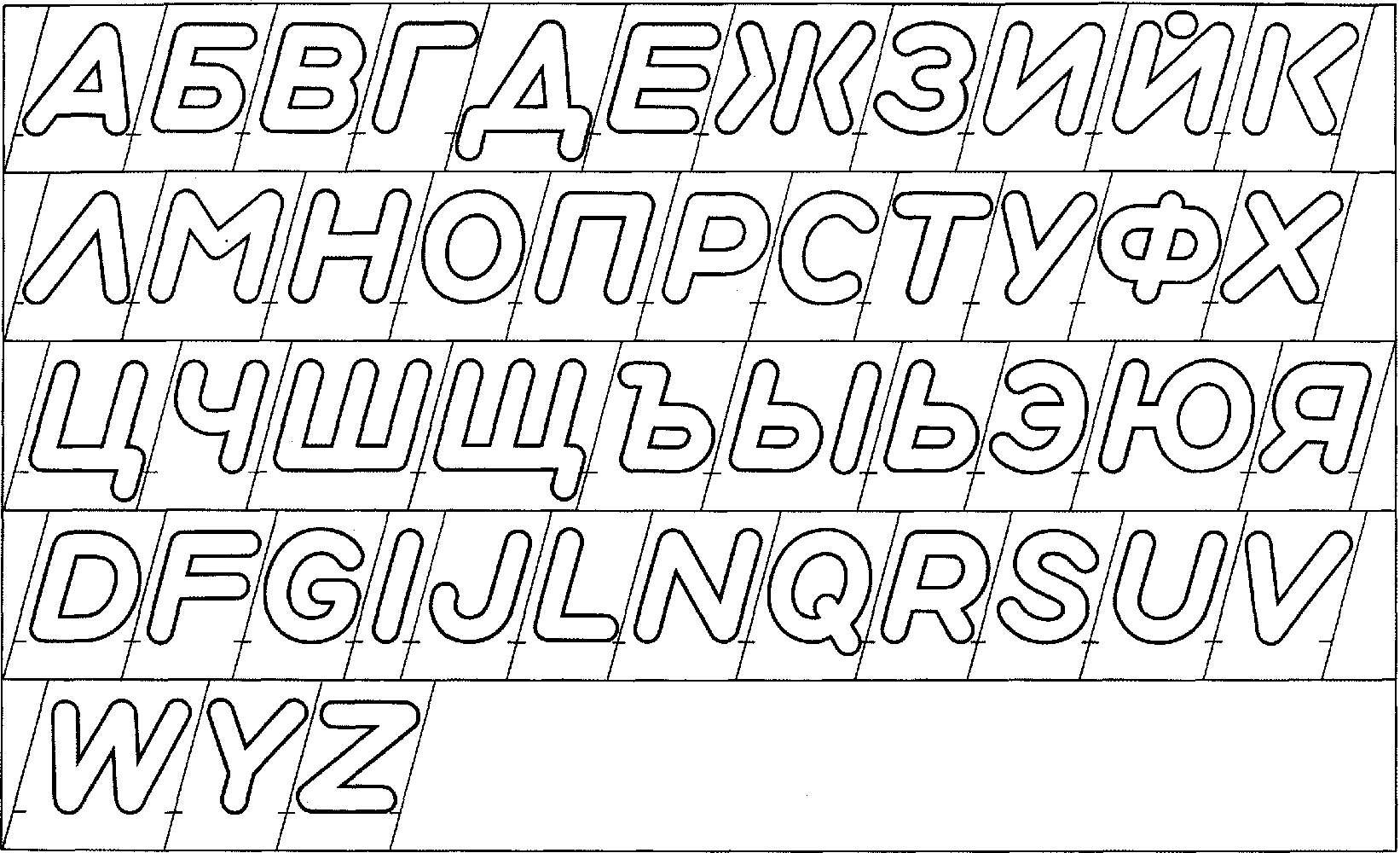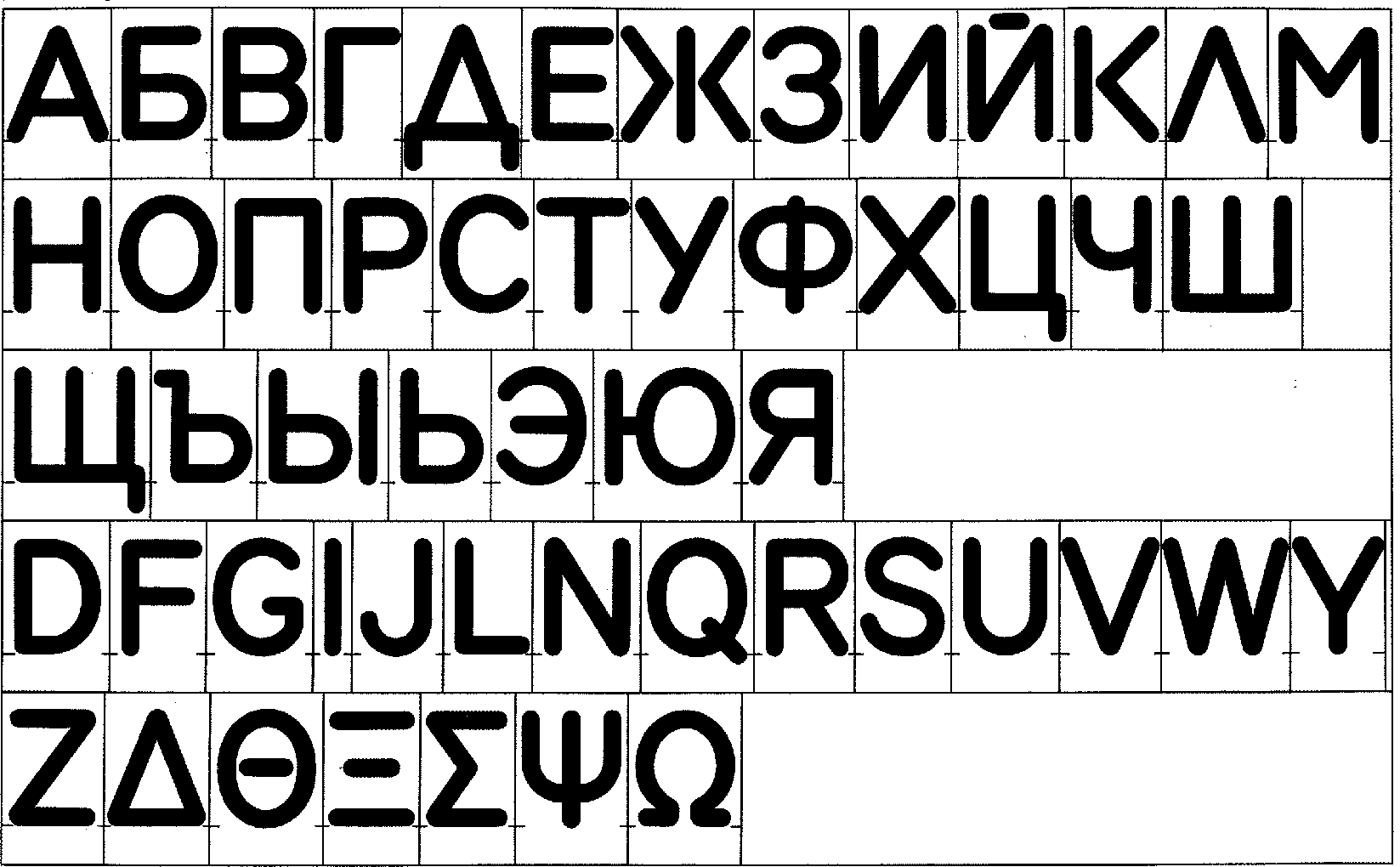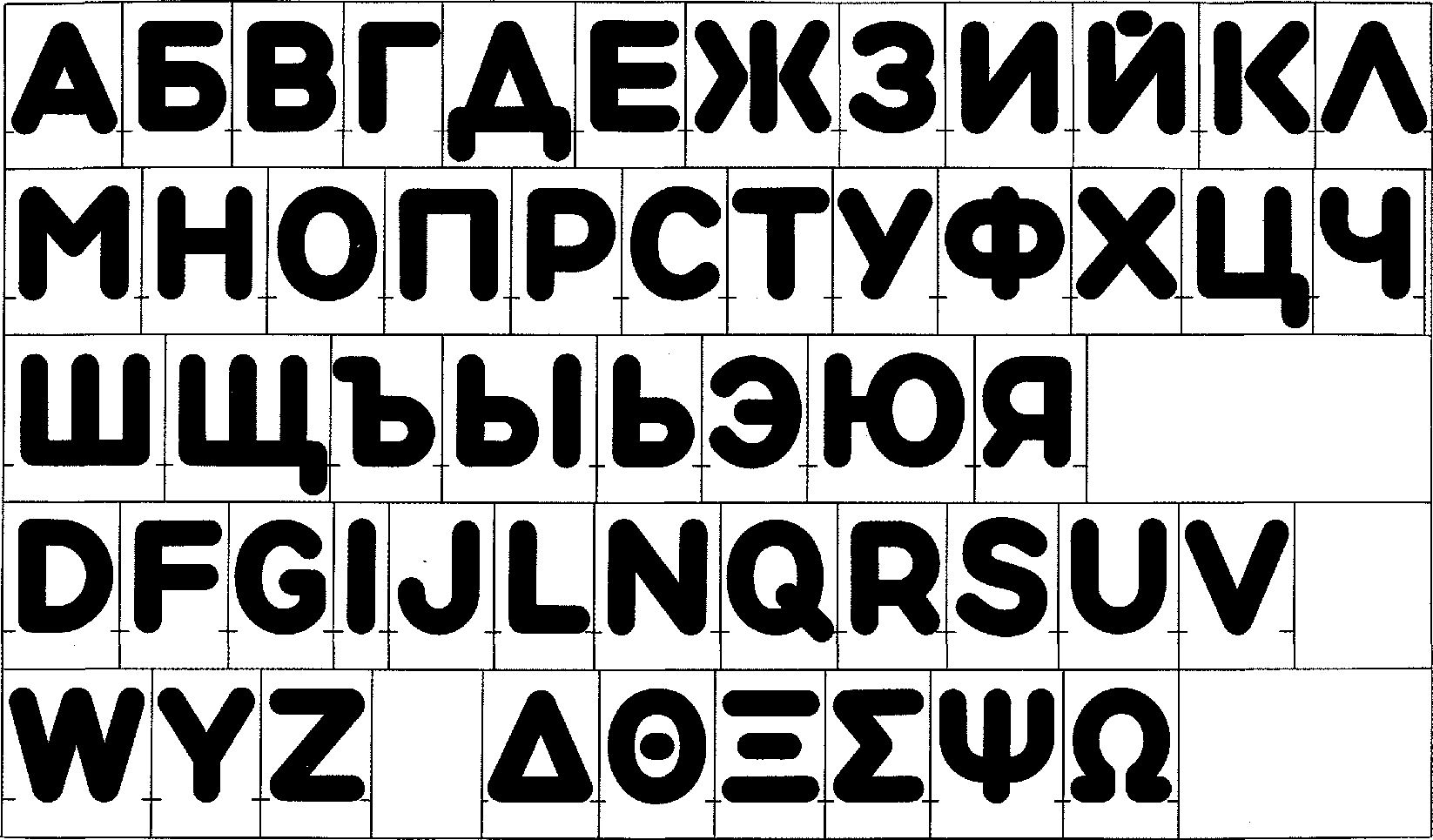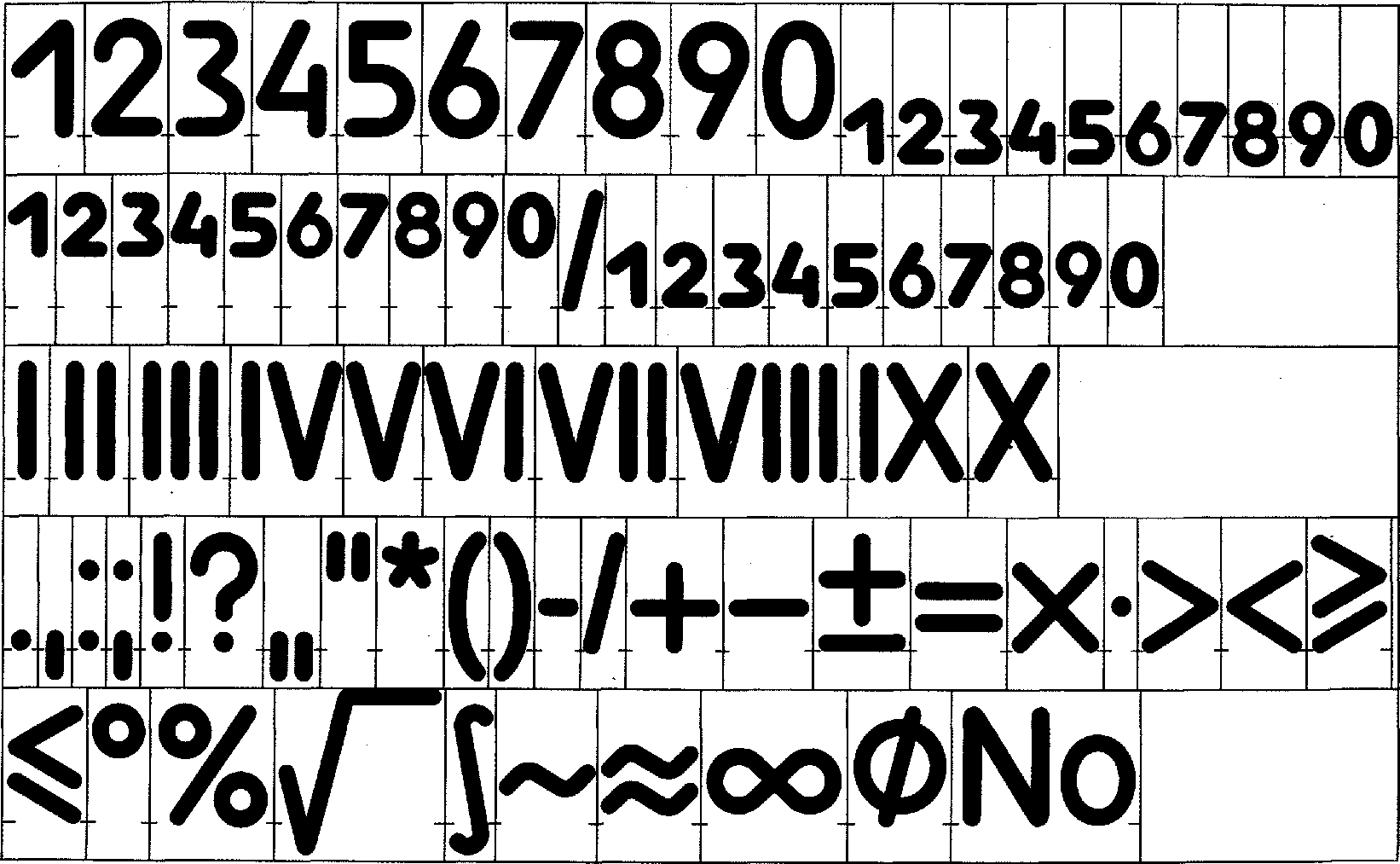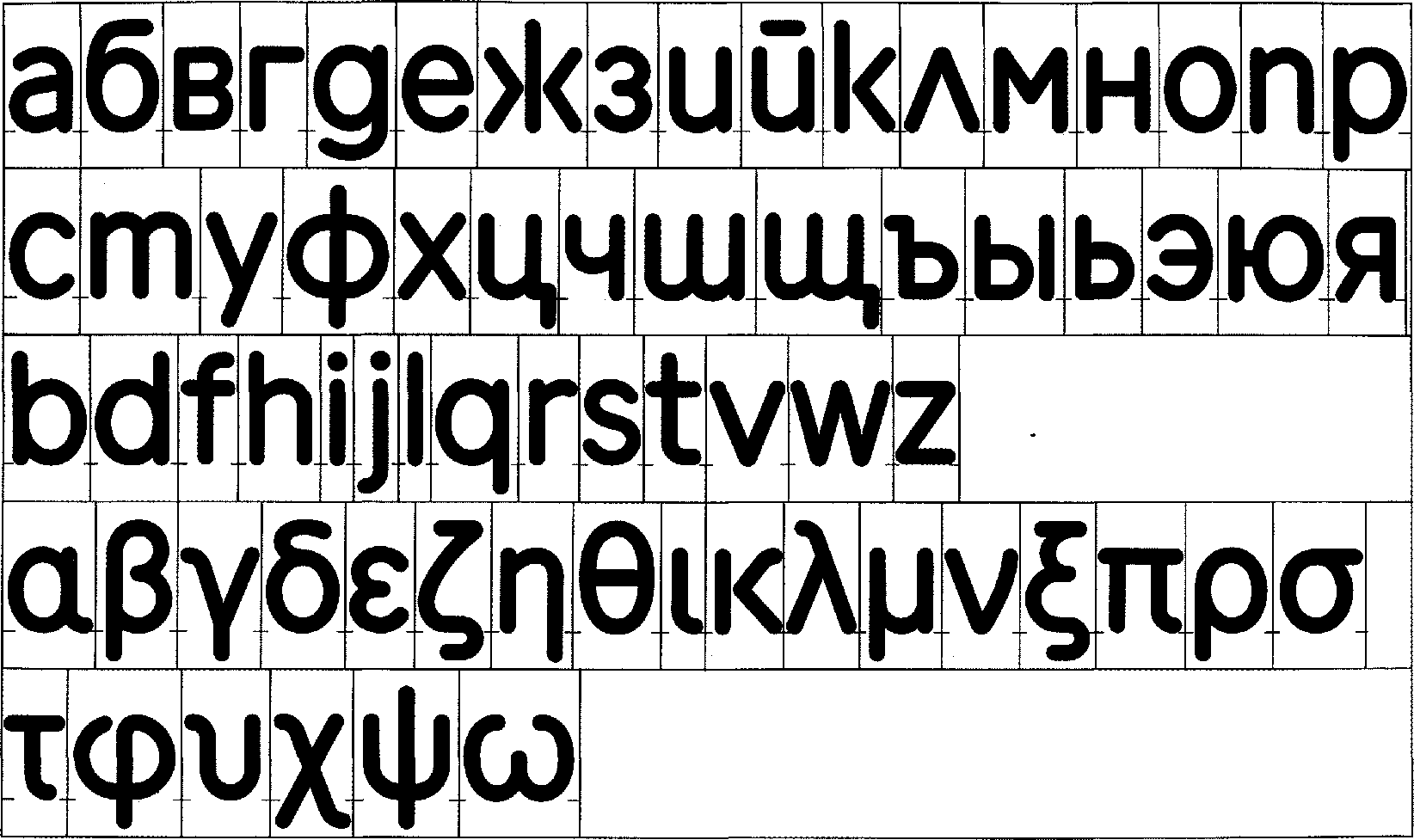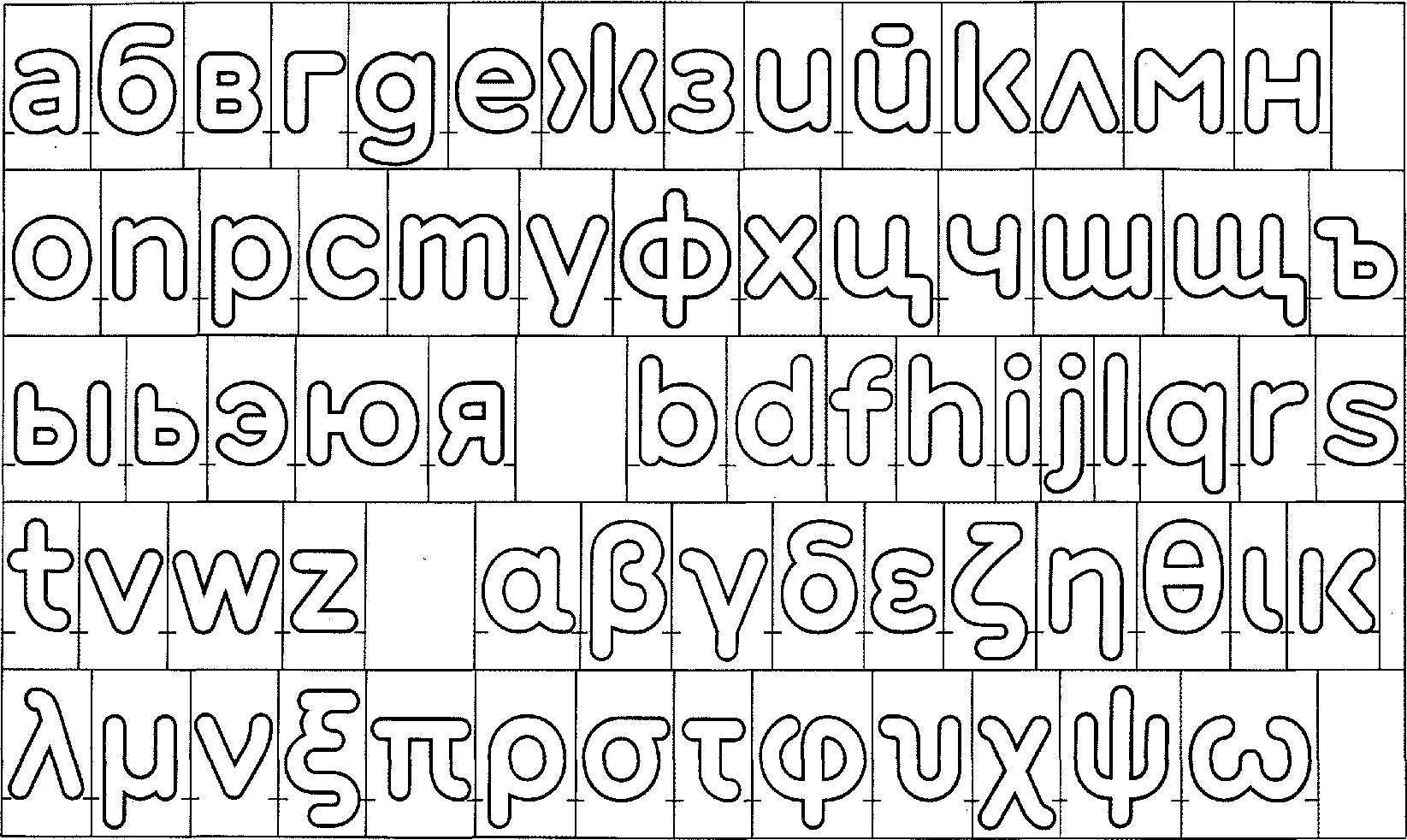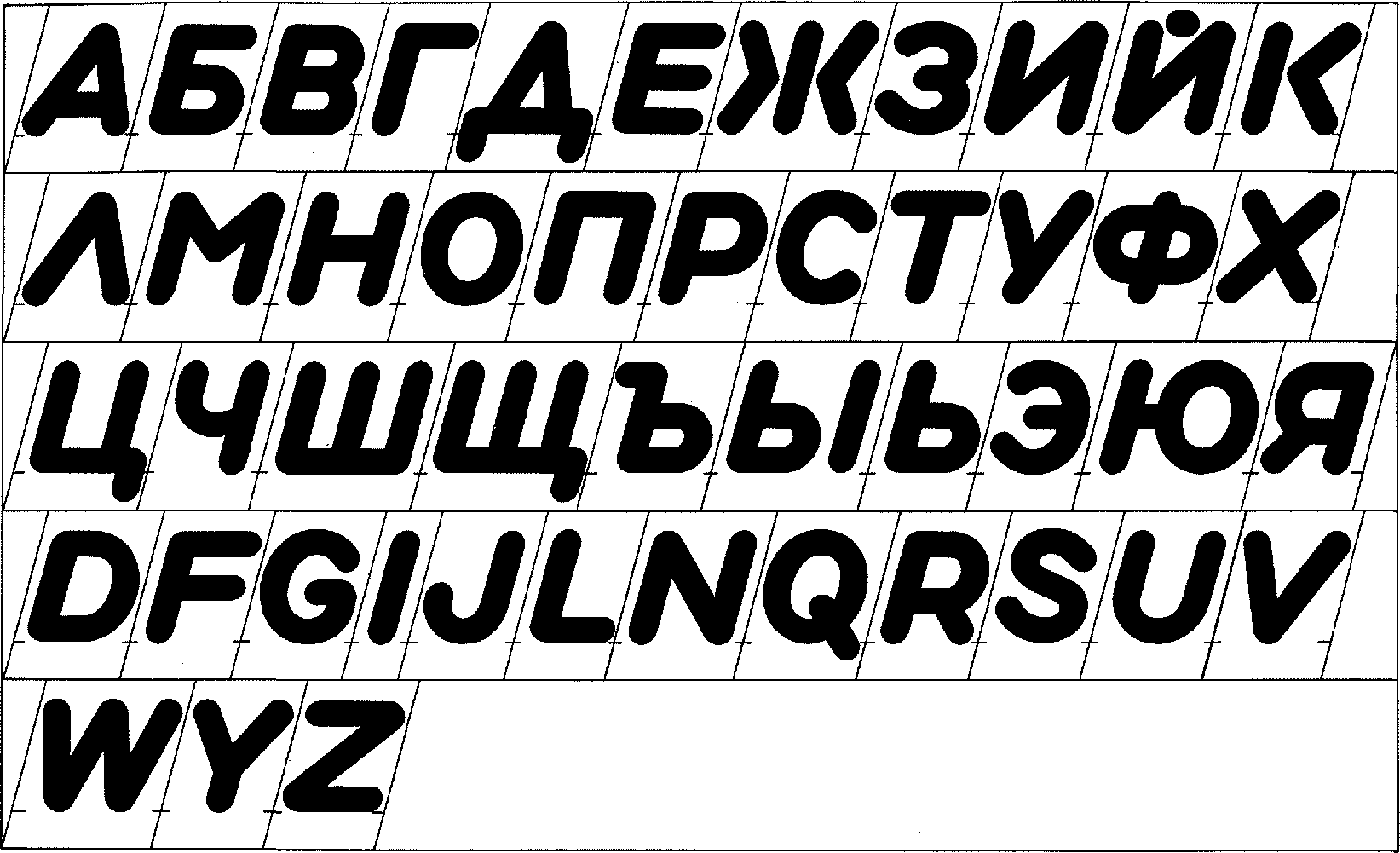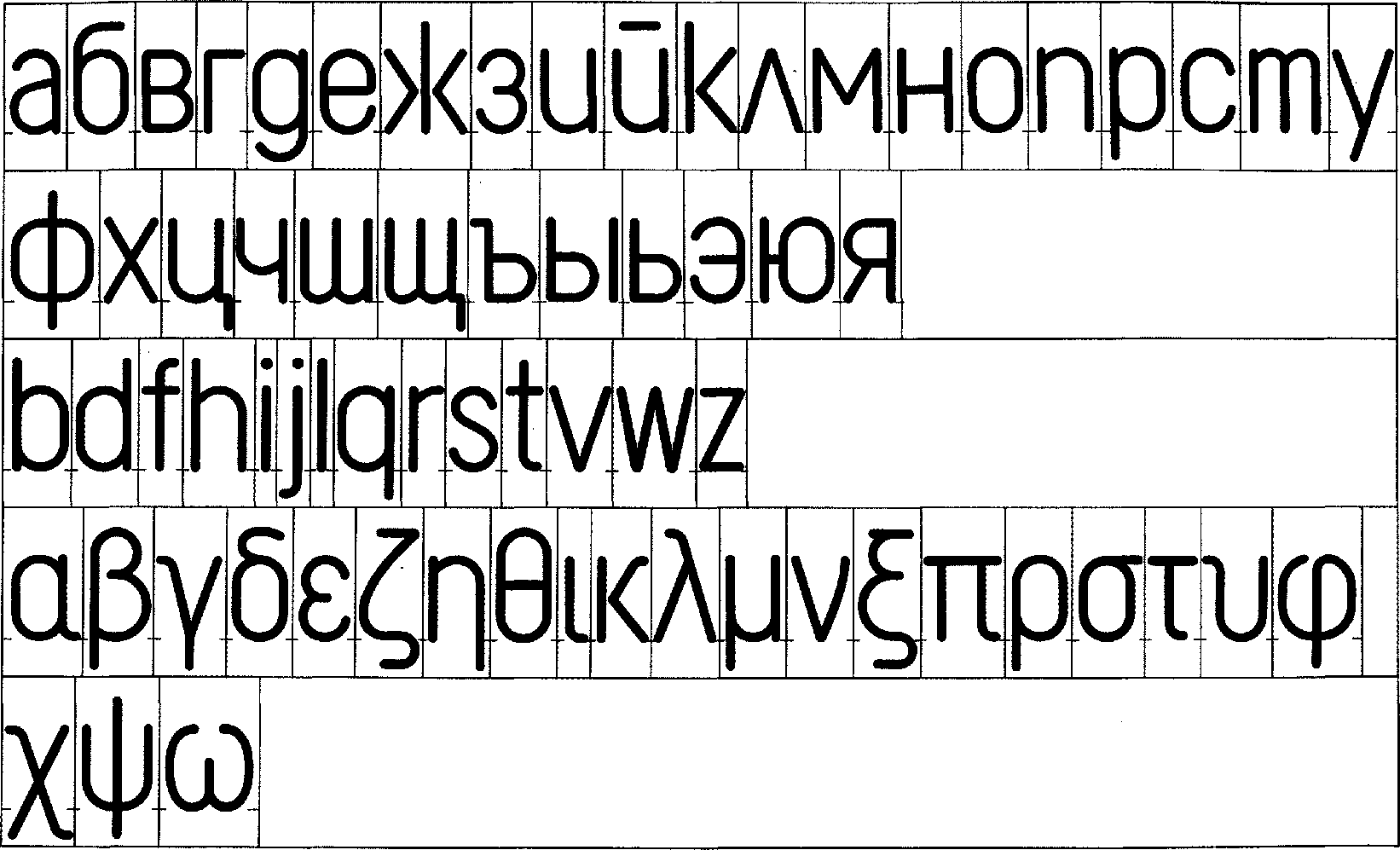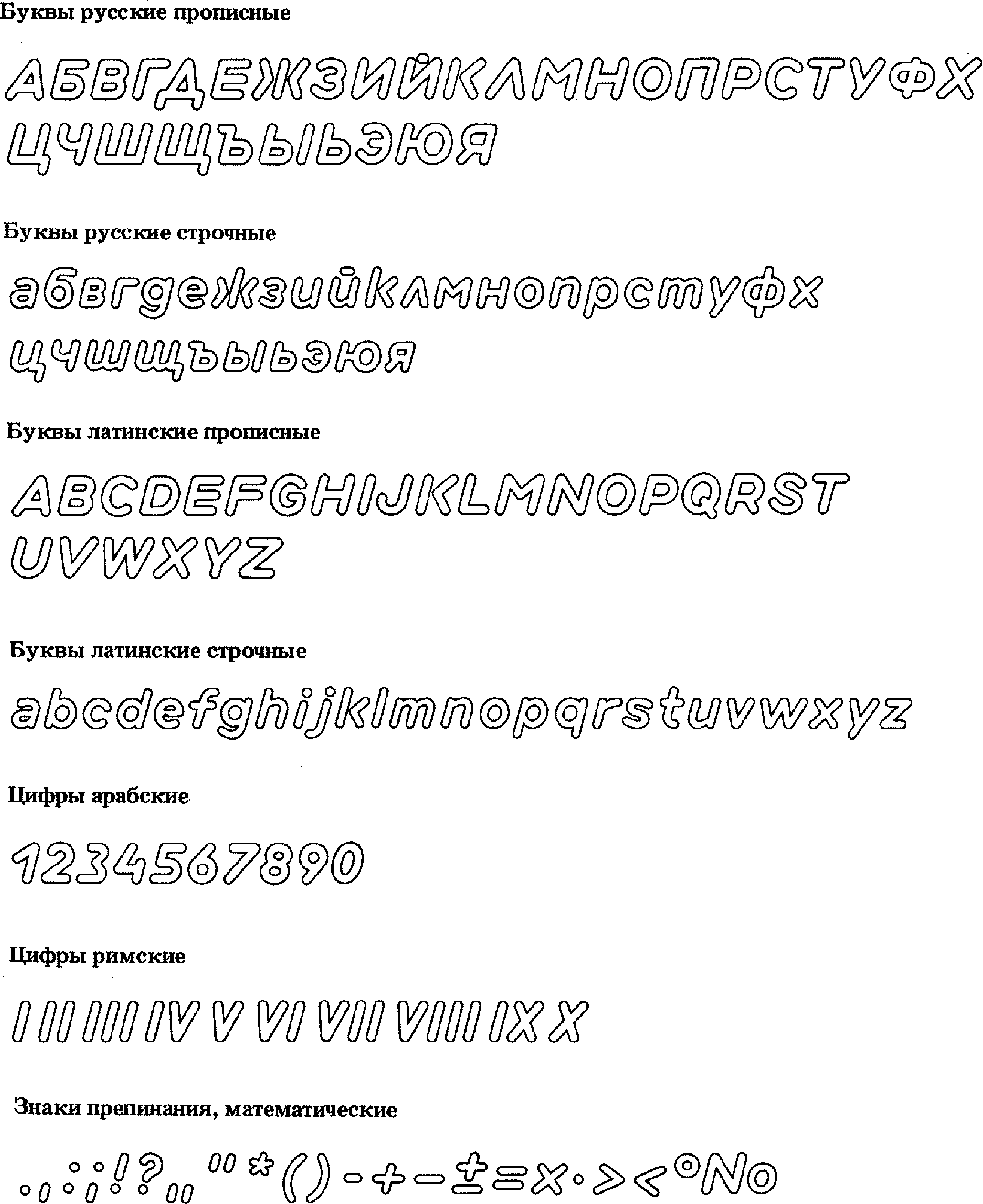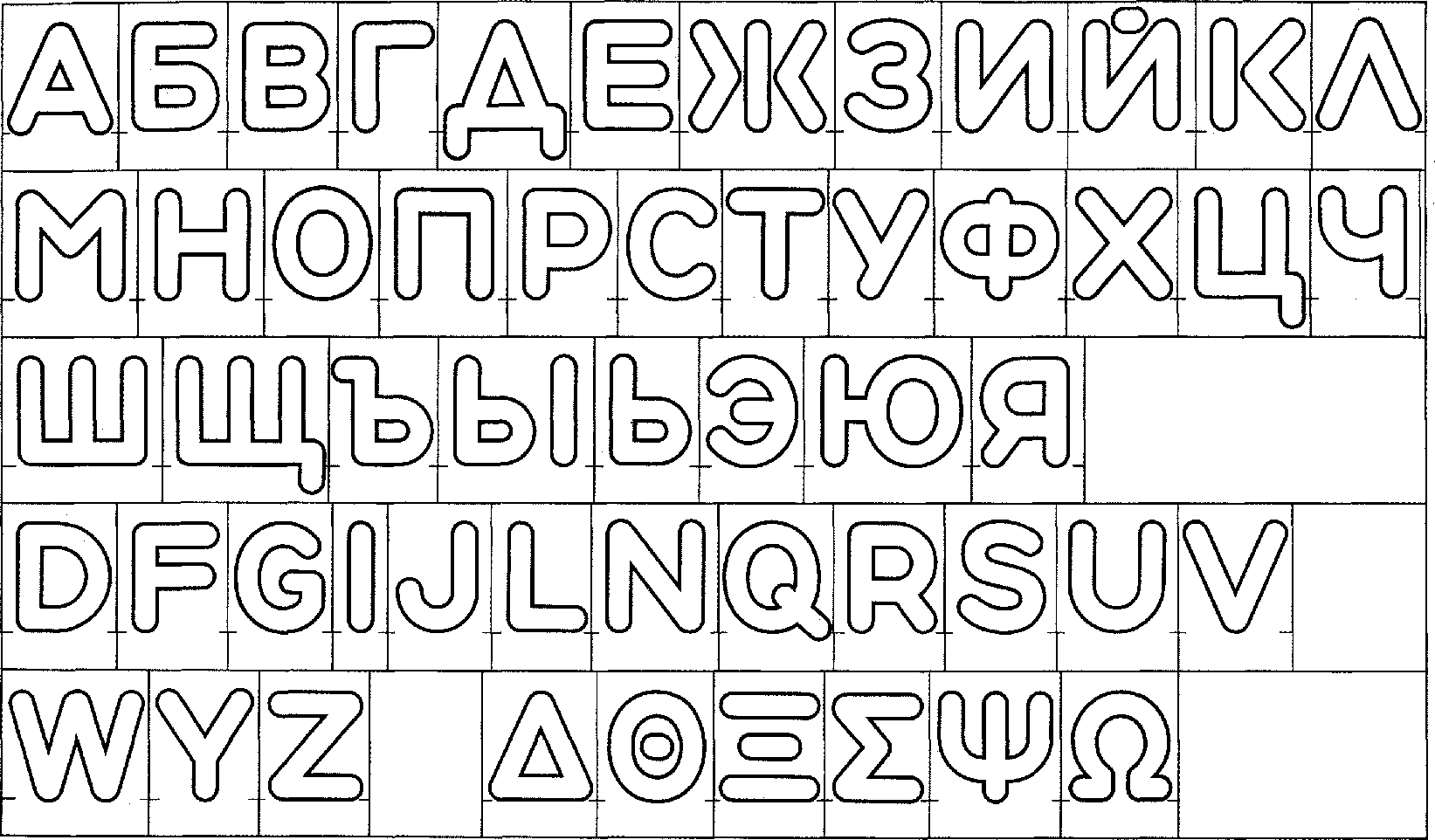
"ГОСТ 26.020-80. Межгосударственный стандарт. Шрифты для средств измерений и автоматизации. Начертания и основные размеры"
МЕЖГОСУДАРСТВЕННЫЙ СТАНДАРТ
ШРИФТЫ ДЛЯ СРЕДСТВ ИЗМЕРЕНИЙ И АВТОМАТИЗАЦИИ
НАЧЕРТАНИЯ И ОСНОВНЫЕ РАЗМЕРЫ
Types for means of measuring and automation.
Inscription and main dimensions
ГОСТ 26.020-80
1. Настоящий стандарт распространяется на шрифты приборной гарнитуры (далее - шрифты) для нанесения надписей методом плоской печати на средства измерений и автоматизации, радиоэлектронную аппаратуру и вычислительную технику и устанавливает начертания и основные размеры. Шрифты допускается использовать для нанесения надписей на упаковке и в сопроводительной документации.
Стандарт не распространяется на шрифты для надписей, наносимых на изделия авиационного приборостроения.
2. Шрифт включает: алфавиты (русский, латинский, греческий); цифры (арабские и римские); знаки (препинания, математические), а также показатели степени, индексы.
3. Шрифты в зависимости от начертания разделяют на:
Пр3 - прямое нормальное полужирное;
Пр41 - прямое узкое светлое;
Пр5 - прямое нормальное жирное;
ПрК5 - прямое контурное;
Пр/5 - наклонное нормальное жирное;
ПрК/5 - наклонное контурное.
4. Шрифт Пр3 - основной шрифт. При дефиците площади и композиционных соображениях допускается использовать шрифт Пр41, а для выделения надписей, обозначающих название, тип, модель прибора и т.п. - шрифты Пр5, ПрК5, Пр/5 и ПрК/5.
5. Размеры шрифтов зависят от высоты
H прописных букв [см. приложение 2
(черт. 1)].
Высоту H выбирают из ряда: 0,6; 0,8; 1,0; 1,2; 1,6; 2,0; 2,5; 3,0; 4,0; 5,0; 6,0; 8,0; 10,0 мм. Дальнейшее увеличение высоты выполняют десятикратным увеличением размеров указанного ряда.
Примечание. Не допускается применять шрифты Пр5, ПрК5, Пр/5, ПрК/5 высотой менее 3 мм.
6. Условное обозначение шрифта должно состоять из слова "шрифт", высоты шрифта, начертания и обозначения настоящего стандарта.
Пример условного обозначения шрифта высотой 5 мм начертания Пр3:
Шрифт 5-Пр3 ГОСТ 26.020-80
НАЧЕРТАНИЯ И СОСТАВ ШРИФТОВ
Пр3 - прямое нормальное полужирное начертание
Черт. 1
Пр41 - прямое узкое светлое начертание
Черт. 2
Пр5 - прямое нормальное жирное начертание
Черт. 3
ПрК5 - прямое контурное начертание
Черт. 4
Пр/5 - наклонное нормальное жирное начертание
Черт. 5
ПрК/5 - наклонное контурное начертание
Черт. 6
(рекомендуемое)
ТРЕБОВАНИЯ К НАДПИСЯМ
1. Надписи набирают путем выклеивания фотооригиналов площадок шрифта крупного размера (например, 10 или 20 мм) с последующим фотоуменьшением выклеенных надписей до необходимого размера.
Площадки, на которых размещены знаки, обеспечивают равномерность и постоянство межбуквенных и межстрочных расстояний.
Расположение шрифтов на площадках для каждого начертания приведено на
черт. 3 -
20.
2. Длина надписи складывается из суммы ширин площадок
(черт. 2). Длину надписи рассчитывают по
Пр/5. Строчные буквы. Расположение на площадках
Черт. 16
Пр/5. Цифры и знаки.
Черт. 17
ПрК/5. Прописные буквы. Расположение на площадках.
Высота шрифта
H = 30 мм; высота площадки
K = 45 мм; ширина площадок
T - по
табл. 4.
Черт. 18
Примечание. При сочетаниях букв типа ГА, ГЛ, ГД, ТА, УЛ и т.д. допускается сокращать интервалы, предусмотренные площадками. Интервал в этом случае выбирают из композиционных соображений.
ПрК/5. Строчные буквы. Расположение на площадках.
Рис. 19
ПрК/5. Цифры и знаки.